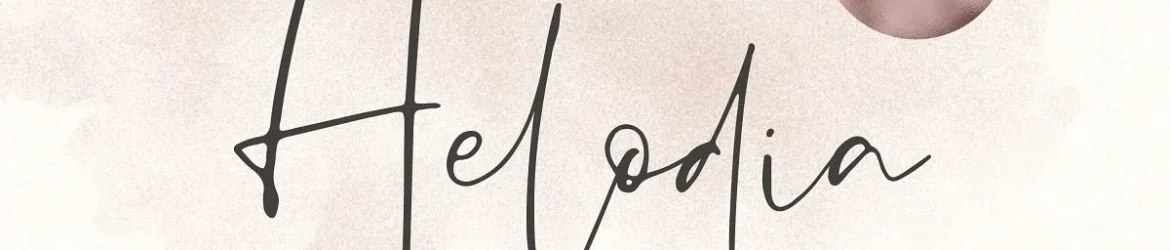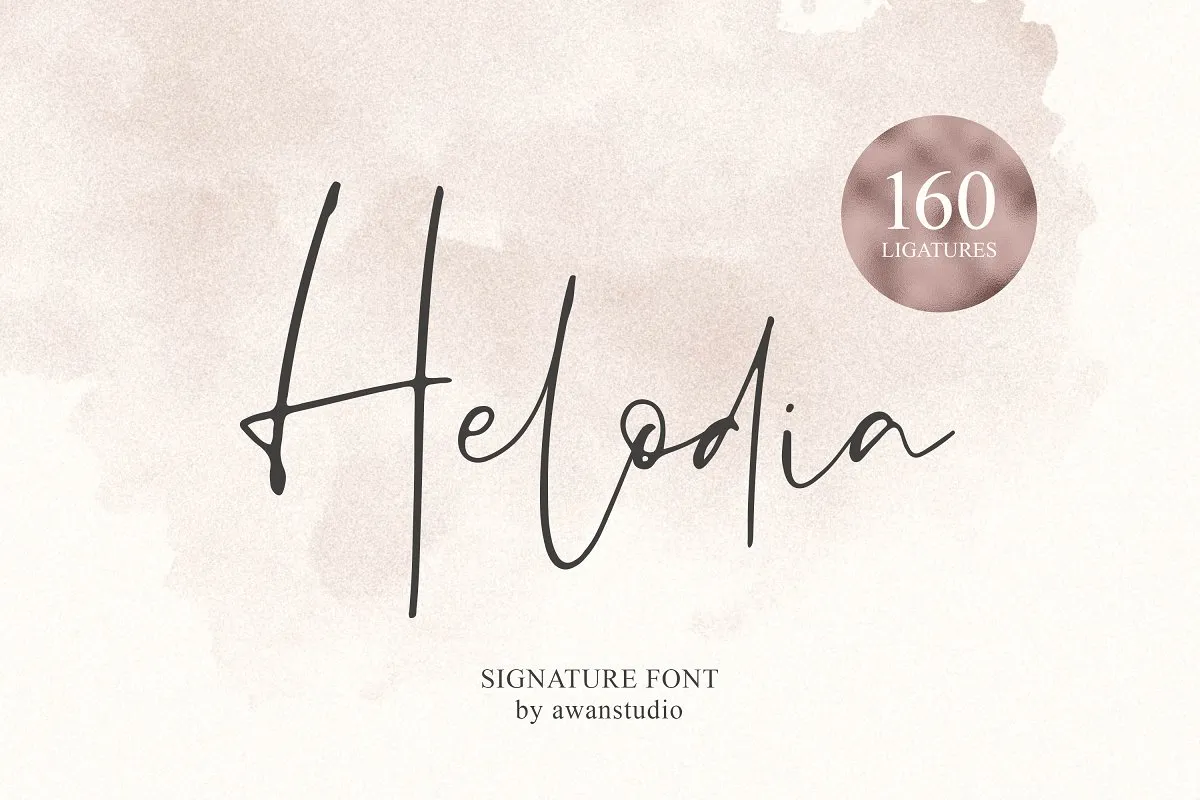
Helodia Signature Font
Introduzimos a Helodia Font, uma nova tipografia digital do tipo mão-dilhada criada pela awan studio. Esta fonte é perfeitamente adequada para quem busca dar um toque único à sua identidade visual e ao design de seu negócio. O Helodia Signature Font permite criar textura de escrita a mano rapidamente, tornando o processo muito mais fácil. Ideal para os requisitos dos cartões de convidado, materiais de marca, cardes de negócios, frases curtas, postagens publicitárias e até mesmo suas próprias marcas digitais, blogs, material de estação, marketing e revistas. Sua sofisticada natureza lhe permite desfrutar de texturas criativas para o seu design pessoal ou comercial. É especialmente adequado para a criação de cartões de casamento, mas também é ideal como um elemento único para qualquer tipo de projeto visual que deseje imprimir com estilo e profissionalismo.